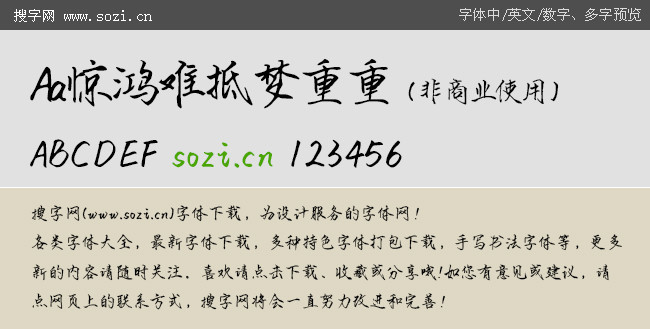
Aa驚鴻難抵夢(mèng)重重(非商業(yè)使用)
搜字網(wǎng)給大家提供一款A(yù)a驚鴻難抵夢(mèng)重重(非商業(yè)使用)中文字體下載,該字體是一款手寫(xiě)中文字體,這款字體筆觸粗細(xì)適中,字形端莊,書(shū)寫(xiě)靈動(dòng)飄逸,適合包裝設(shè)計(jì)、書(shū)裝設(shè)計(jì)、海報(bào)設(shè)計(jì)等應(yīng)用(此字體為個(gè)人非商用版,商用可以聯(lián)系QQ:1006760504)。